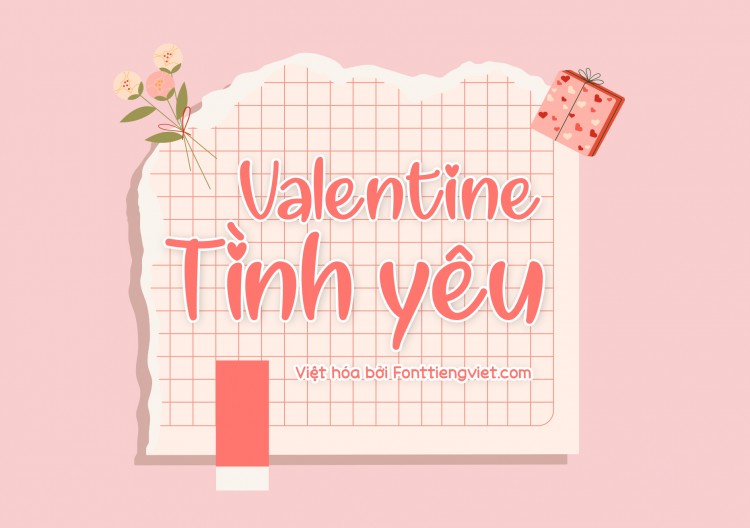
Font việt hóa 1FTV Liebe Finden phong cách Valentine
Font việt hóa 1FTV Liebe Finden phong cách Valentine lãng mạn cho thiết kế đồ họa
Giới thiệu về Font việt hóa 1FTV Liebe Finden phong cách Valentine
Trong thế giới thiết kế đồ họa, việc lựa chọn Font Miễn Phí phù hợp đóng vai trò quan trọng trong việc truyền tải cảm xúc của tác phẩm. Đặc biệt vào những dịp lễ ý nghĩa như Ngày lễ tình nhân, Font việt hóa 1FTV Liebe Finden phong cách Valentine trở thành một công cụ đắc lực giúp các bạn học sinh và thầy cô tạo ra những món quà tinh thần tuyệt vời. Đây là một bộ phông chữ mang đậm nét viết tay thủ công, gợi lên sự chân thành, mộc mạc nhưng không kém phần tinh tế. Với đường nét thanh mảnh và những nét uốn lượn mềm mại, Liebe Finden không chỉ đơn thuần là các ký tự mà còn là ngôn ngữ của trái tim. Phiên bản 1FTV đã được tối ưu hóa hoàn toàn cho tiếng Việt, giúp người dùng dễ dàng sử dụng trong các phần mềm thiết kế phổ biến mà không lo lỗi hiển thị hay thiếu hụt các ký tự dấu đặc trưng.
Những đặc điểm nổi bật của Font việt hóa 1FTV Liebe Finden phong cách Valentine
Phong cách thiết kế chữ viết tay độc đáo
Điểm khác biệt lớn nhất của Font việt hóa 1FTV Liebe Finden phong cách Valentine chính là sự tự nhiên trong từng nét bút. Không giống như các phông chữ máy tính cứng nhắc, bộ phông này mô phỏng lại cách viết tay của con người với những biến tấu ngẫu hứng. Điều này tạo cảm giác gần gũi, giúp người xem cảm nhận được sự ấm áp và tâm huyết mà người thiết kế gửi gắm vào sản phẩm. Đối với các bạn học sinh, đây là lựa chọn lý tưởng để trang trí báo tường, làm thiệp tặng bạn bè hoặc thiết kế các bài trình chiếu kỷ niệm lớp học thêm phần sinh động và đầy cảm xúc lãng mạn.
Khả năng ứng dụng đa dạng trong giáo dục và đời sống
Mặc dù mang tên gọi phong cách Valentine, nhưng tính ứng dụng của bộ chữ này còn rộng lớn hơn thế. Bạn có thể sử dụng nó cho các tiêu đề sách, bìa sổ tay, hay các biển hiệu nhỏ trong không gian học tập. Trong môi trường học đường, giáo viên có thể dùng phông chữ này để làm nổi bật các câu danh ngôn về tình yêu thương, lòng nhân ái hoặc tạo các chứng nhận khen thưởng có phong cách nghệ thuật. Sự mềm mại của các ký tự giúp giảm bớt vẻ khô khan của các văn bản hành chính thông thường, mang lại một luồng gió mới cho các tài liệu học tập hàng ngày.
Lưu ý khi phối hợp màu sắc và bố cục
Để Font việt hóa 1FTV Liebe Finden phong cách Valentine phát huy tối đa vẻ đẹp, bạn nên kết hợp với những gam màu nhẹ nhàng như hồng pastel, đỏ thẫm hoặc trắng kem. Về mặt bố cục, phông chữ này thường đẹp nhất khi được đặt làm tiêu đề chính hoặc các đoạn trích dẫn ngắn. Tránh sử dụng bộ chữ cho các đoạn văn bản dài vì các nét uốn lượn có thể gây mỏi mắt cho người đọc. Một mẹo nhỏ là hãy tăng khoảng cách giữa các dòng để các nét chữ không bị chồng chéo, giữ cho thiết kế luôn sạch sẽ và chuyên nghiệp.
Kết luận về giá trị nghệ thuật của bộ font
Tổng kết lại, việc sở hữu bộ Font việt hóa 1FTV Liebe Finden phong cách Valentine sẽ giúp kho tài nguyên thiết kế của bạn trở nên phong phú và có chiều sâu hơn. Đây không chỉ là một phông chữ, mà là cầu nối giúp những lời chúc tốt đẹp trở nên lung linh và ý nghĩa hơn bao giờ hết. Hy vọng rằng với chia sẻ từ Font Miễn Phí, Font Việt Hóa, Font việt hóa 1FTV Liebe Finden phong cách Valentine, bạn sẽ có thêm cảm hứng để tạo nên những tác phẩm tuyệt vời dành tặng cho những người thân yêu xung quanh mình.